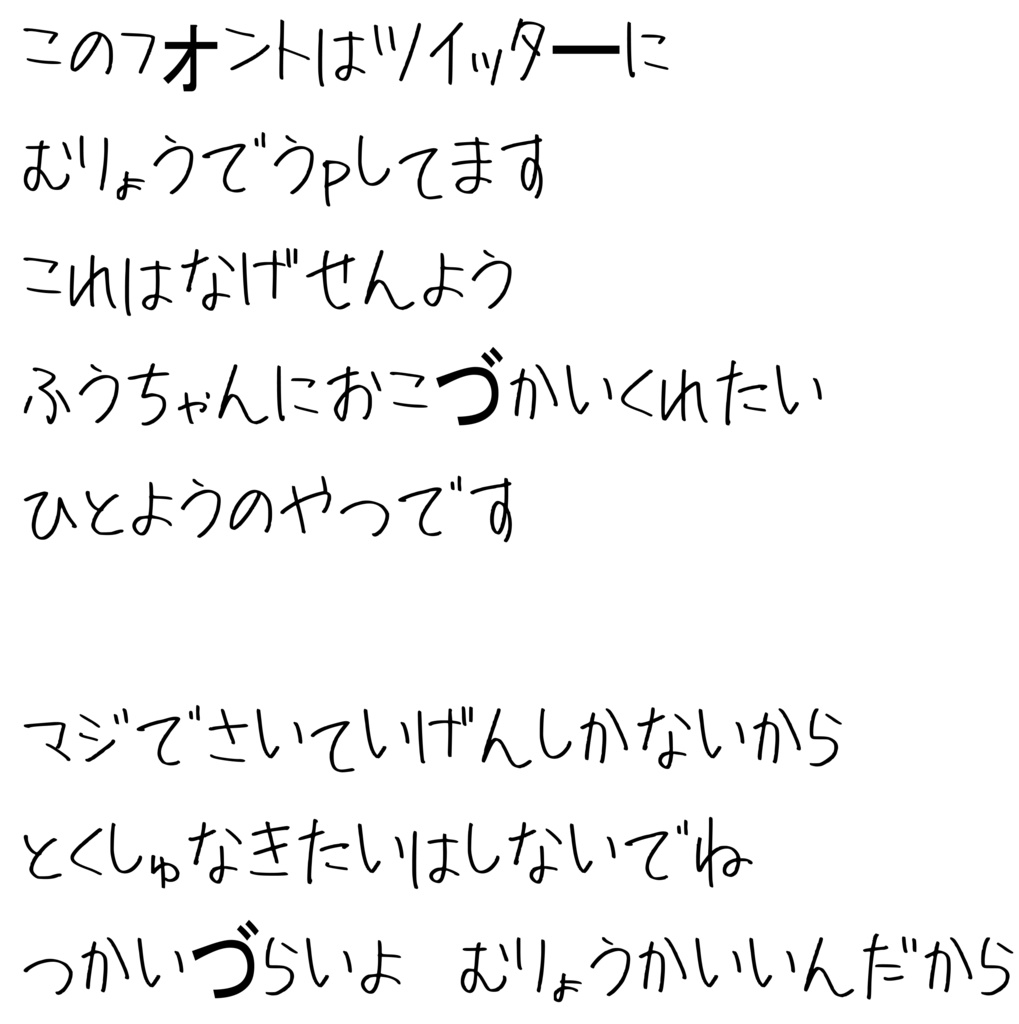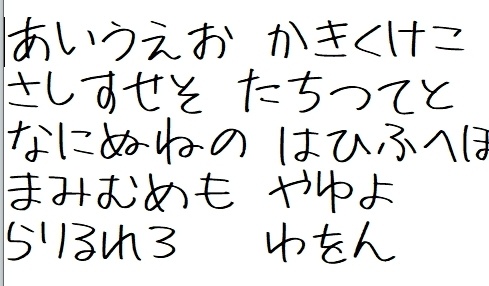
ふうちゃんフォント
ふうちゃんの手書き文字に若干の需要が数年前よりありそうだったので。 フッ軽で生きていきたいと思った。だから作った。 フォントファイルは二種類あるのである。 こっちだと両方あるよ。でもツイッターなら無料だよ。 ※無料会員で作ったからマジで最低限だけだよ※ ※ひらがなとカタカナと英語数字は全部別れてます※ ※サイズ調整したつもりだけどガバい※ ※一部の文字は一部の記号に代替されています。主に、あんま使わなさそうな文字とか※ 「あ」と「ん」がかわいいのでオススメです。 ツイッターにうpしてないおまけもあるよ。 ほんとにおまけだから期待しないでね:) フォントはご自由にお使いください。 わたしが困るようなことになる使い方はご遠慮ください。 商用同人お好きにどうぞ、再配布と販売、自作発言は禁止します。 ノリで作ったフォントだのでいろいろなところはご了承ください。